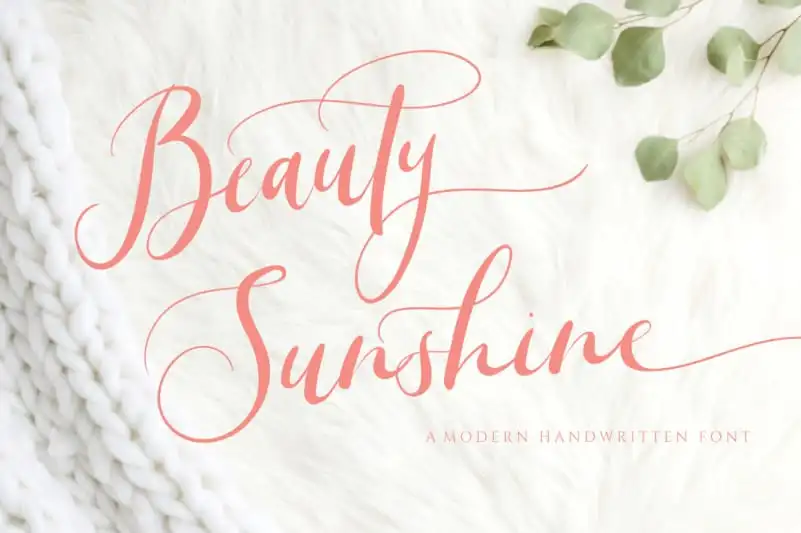
Beauty Sunshine Calligraphy Font – Fonte Grátis
Beauty Sunshine Calligraphy Font
A Beauty Sunshine Calligraphy Font é uma fonte elegante e delicada projetada para adicionar uma dose extra de luxo aos seus trabalhos de design. Esta fonte foi criada para quem aprecia um estilo que se destaca, com sua mão livre e natural expressando uma beleza única. Este recurso PUA permite que você acesse facilmente todos os símbolos e as formas alternativas desta fonte. Perfeita para designers procurando por um toque de sofisticação em qualquer projeto, esta Beauty Sunshine Calligraphy Font adicionará um brilho luxuoso à sua identidade visual. O PUA Encoding é especialmente útil porque permite que você use com facilidade todos os detalhes do design da fonte, desde as formas básicas até as formas alternativas mais elaboradas. Seja para criar cartões de apresentação, adesivos personalizados ou qualquer outro projeto gráfico, este recurso não apenas fará a diferença, ele ajudará a destacar sua marca. Sua elegância e delicadeza garantem que ela seja perfeita tanto para design gráfico quanto para criação de materiais de preservação digital. A Beauty Sunshine Calligraphy Font é uma opção perfeita para aqueles que buscam um toque único e luxuoso em suas publicações digitais ou impressos.